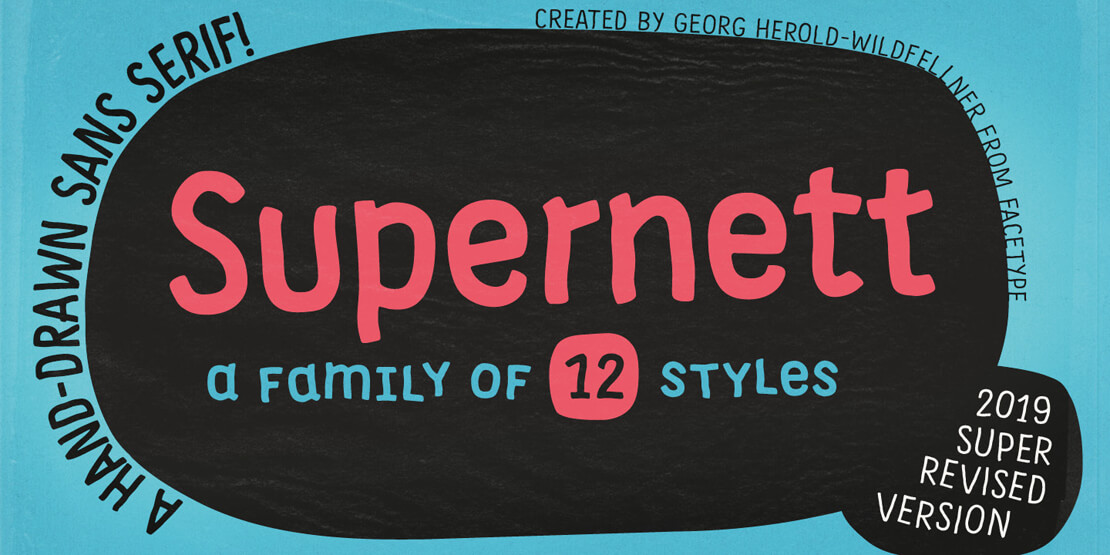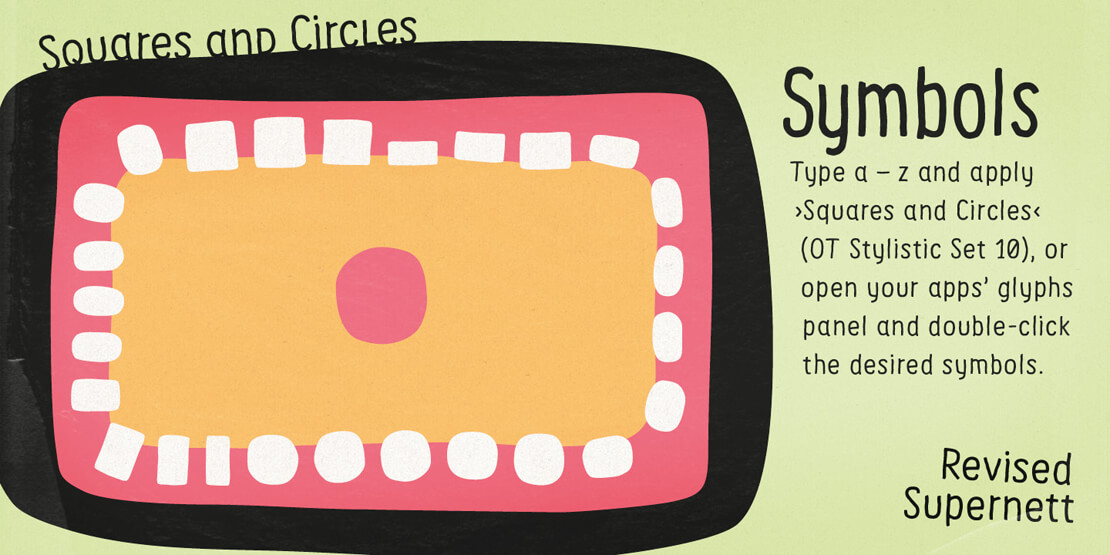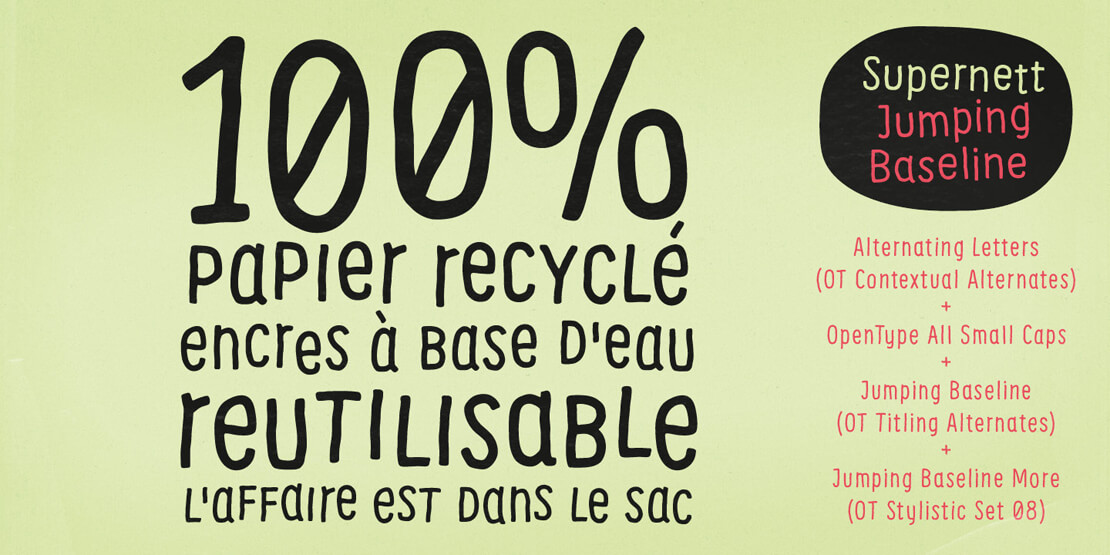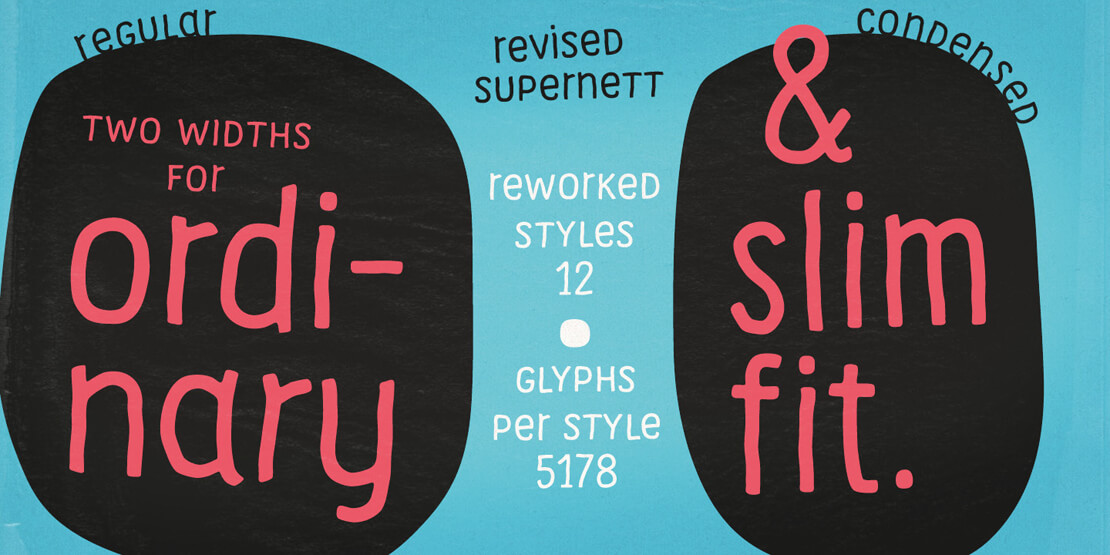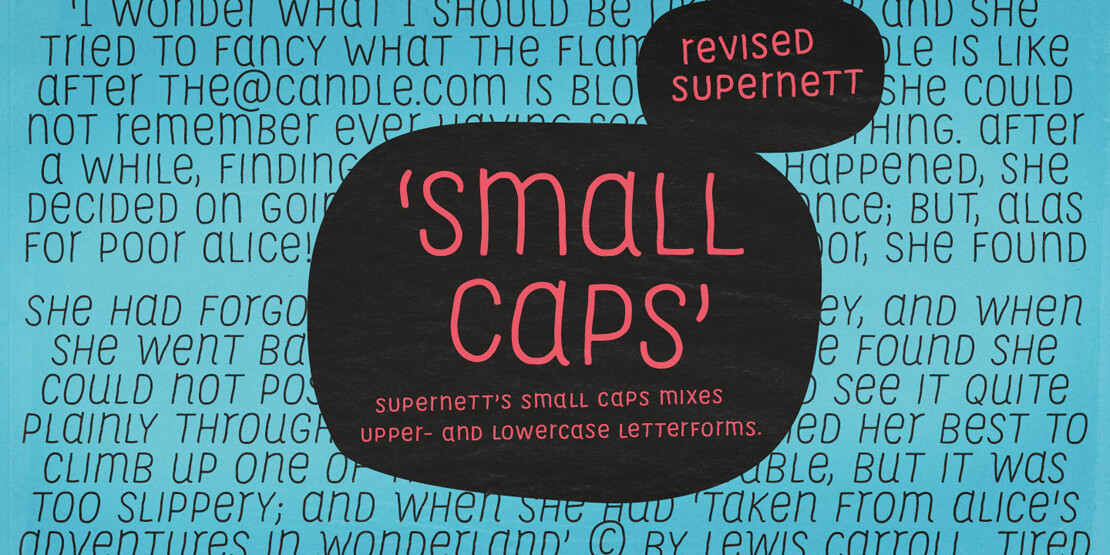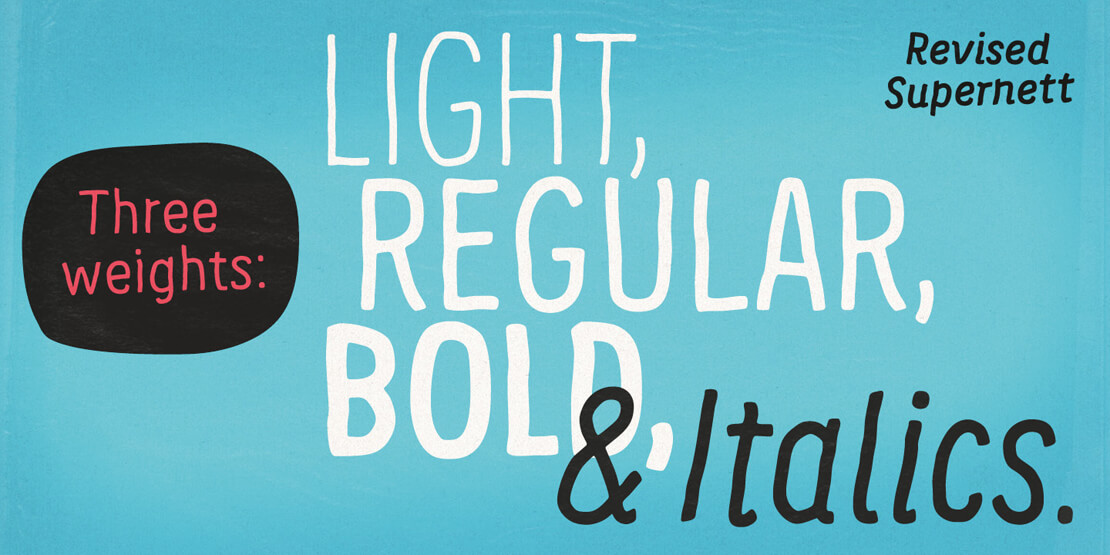
»Supernett« ist jetzt noch netter
Einfach nett und richtig handgemacht, die neue »Supernett« von Georg Herold-Wildfellner. Die Schriftfamilie bietet pro Font über 5.000 unterschiedliche Zeichen, die sich per Zufallsprinzip beim Schreiben abwechseln. Mit Gratis-Font zum Herunterladen!
Für jeden der Schnitte liegen die Buchstaben und Ziffern jeweils in drei Varianten vor. Eines der Hauptmerkmale von »Supernett« ist außerdem das »Wackeln und Zappeln« von Zeichen, das für Variationen im Schriftbild sorgt.
Buchstaben springen geradezu um die Grundlinie herum und neigen sich mal vor- oder rückwärts. Kombiniert mit den entsprechenden Opentype-Funktionen wirkt die Schrift dann so, als wäre sie von Hand geschrieben.
Handgeschrieben und platzsparend
Die »Supernett« ist eine Text- und Display-Schriftfamilie. Sie eignet sich zudem für platzsparende Überschriften und Texte auf kleinstem Raum. 12 Schnitte sind enthalten.
Die Schrift gibt es in »Light«, »Regular« und »Bold« mit ergänzenden Italics-Fonts. Außerdem steht die »Supernett« als Condensed-Variante ebenfalls in »Light«, »Regular« und »Bold« mit entsprechenden Kursiven bereit.